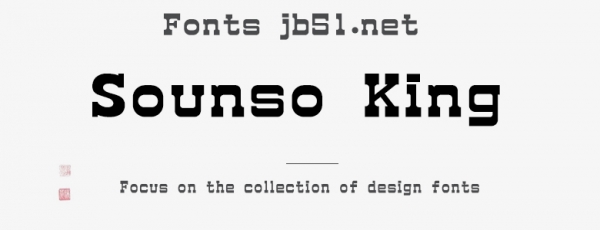
Sounso King是由上首造字出品的英文字體,這款字體筆劃粗重,橫豎筆進(jìn)行了簡化,整體筆劃做了粗細(xì)變化,在基礎(chǔ)字形的基礎(chǔ)上做了襯線裝飾,字體整體穩(wěn)重大氣的氣質(zhì),適合應(yīng)用于藝術(shù)設(shè)計、平面宣傳設(shè)計、網(wǎng)頁設(shè)計,書法字帖等領(lǐng)域。